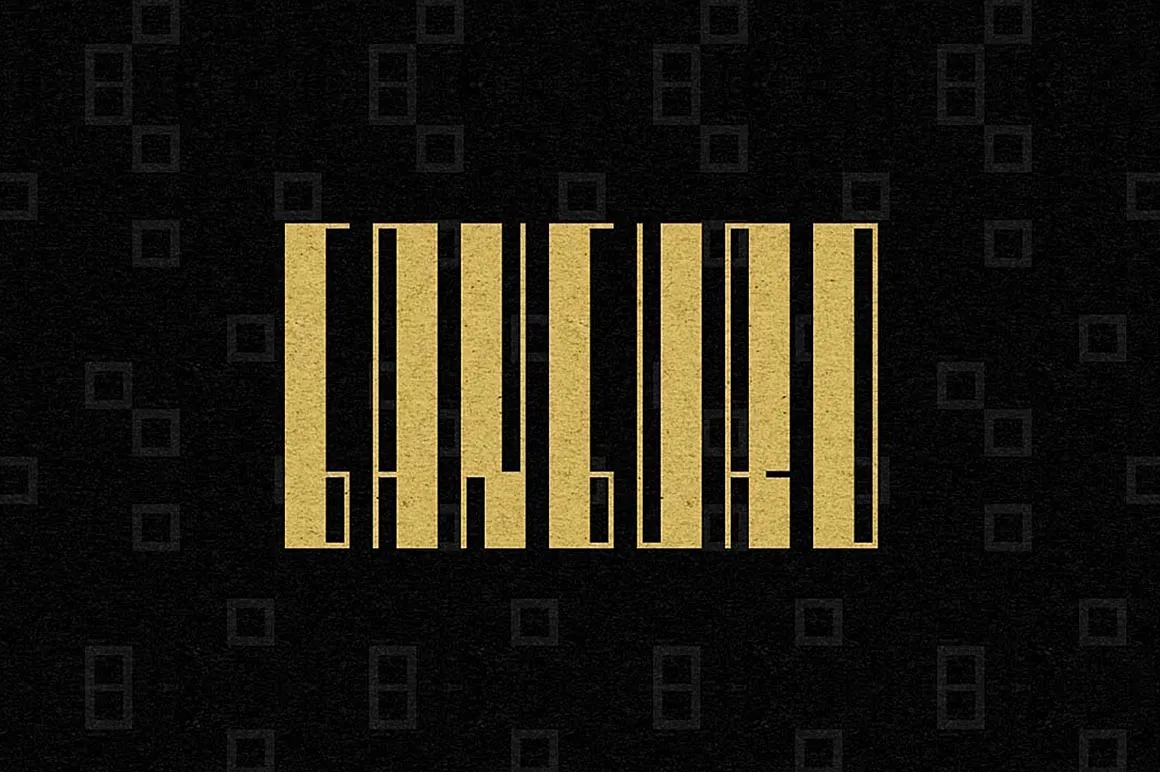
Ganguro Font – Download Grátis
Esta fonte Retro Ganguro é uma criação única do designer Hamilton. Ela adota um estilo geometrico ou futurista e foi desenvolvida pela Ezeqviel Ergo. Se você está procurando por algo diferente para dar uma roupagem retro a suas criações, essa fonte pode ser perfeita. É feita em formato de custom font que permite ajustes personalizados. Para aqueles que apreciam estilos arcaicos ou futuristas, esta é uma escolha certa. Descarregue e divirta-se com seu novo adorno gráfico.